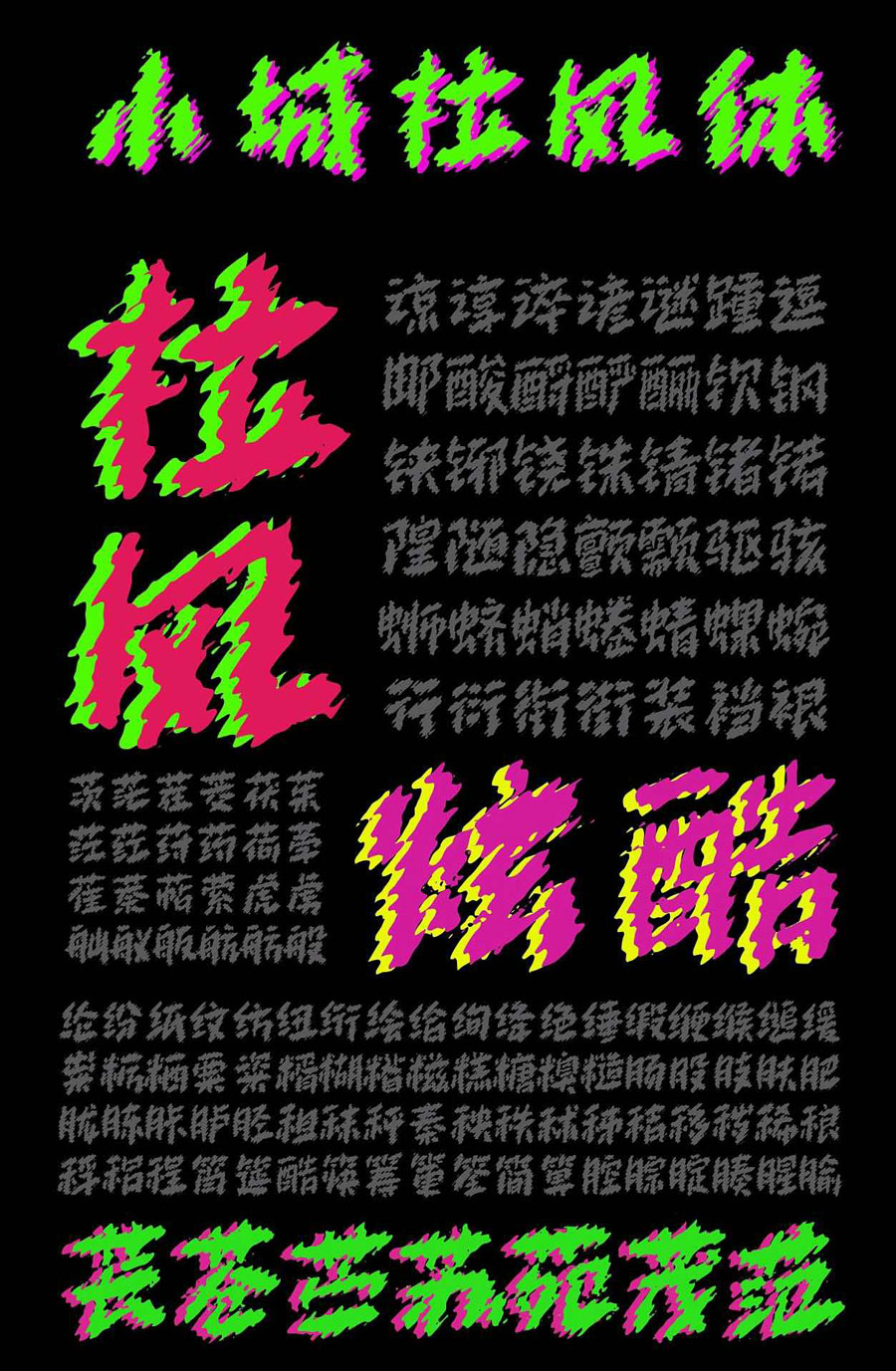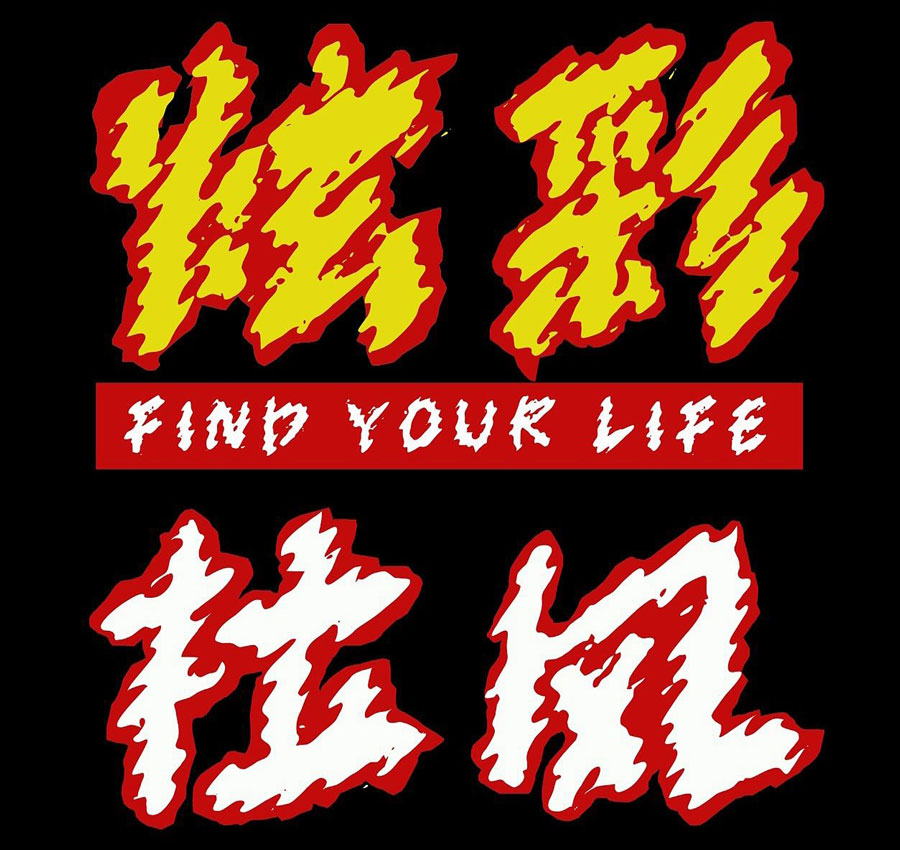
小城拉风体
小城拉风体是小城字库的第一款免费商用字库,是一款速度炫酷炫彩风格的手写字库,适合潮流炫酷类的海报主标题和街头服饰印花等场景。
小城拉风体是由小城字库于 2026 年 3 月 15 日发布的一款免费可商用的中文手写艺术字体。设计上打破了传统字体的规整感,通过波浪形笔画和动态线条,营造出“被风吹过”的流动感,视觉冲击力很强。
小城拉风体
小城拉风体完整支持 GB2312 简体字库,涵盖 6763 个常用汉字和部分标点符号总计 7212 个字符,很适合潮流炫酷类的海报主标题和街头服饰印花等场景。